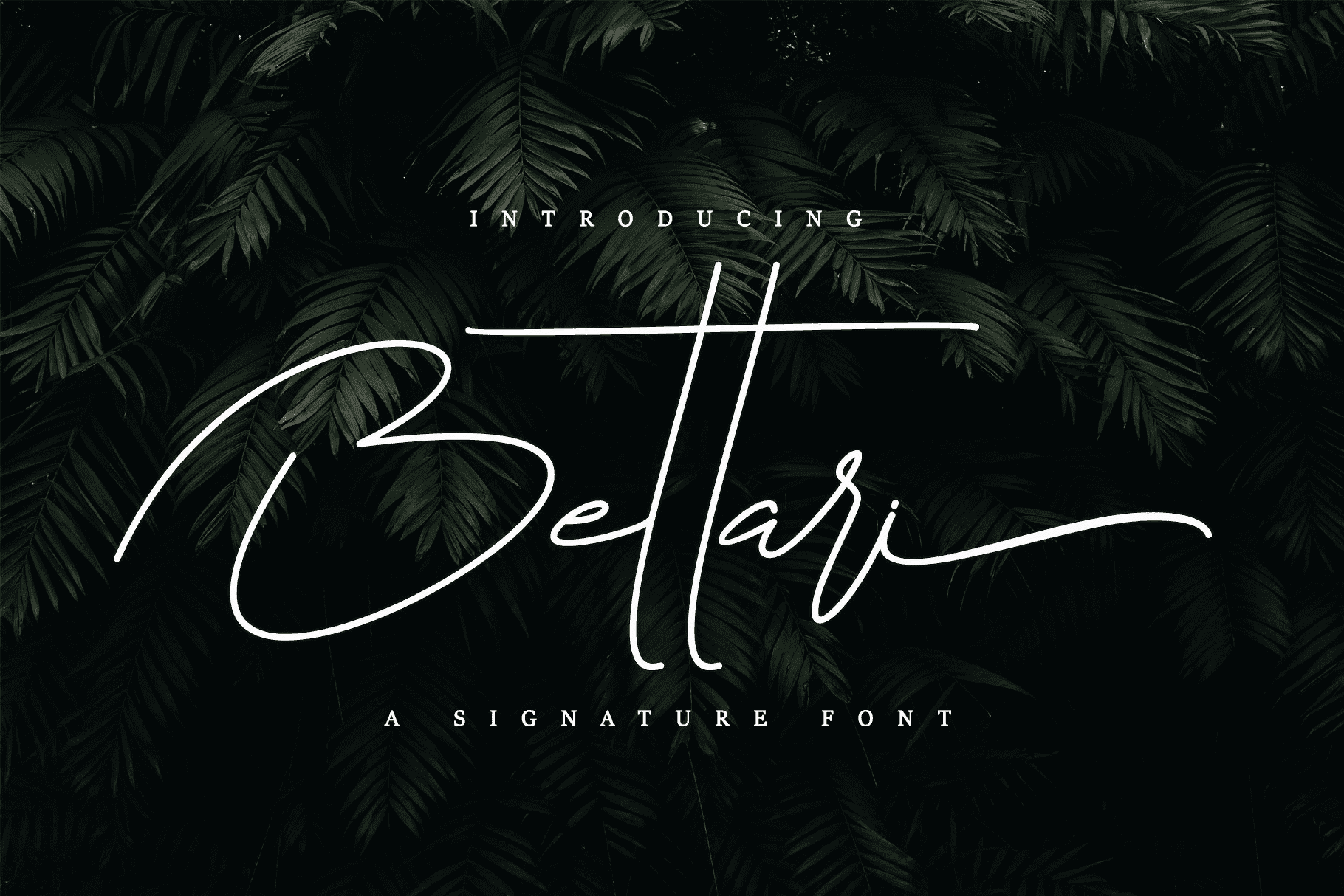
Bettari
- это фирменный шрифт с красивыми штрихами и лигатурами.
Он потрясающе смотрится на свадебных приглашениях, благодарственных открытках, цитатах, поздравительных открытках, логотипах, визитных карточках и любом другом дизайне, требующем рукописного штриха.